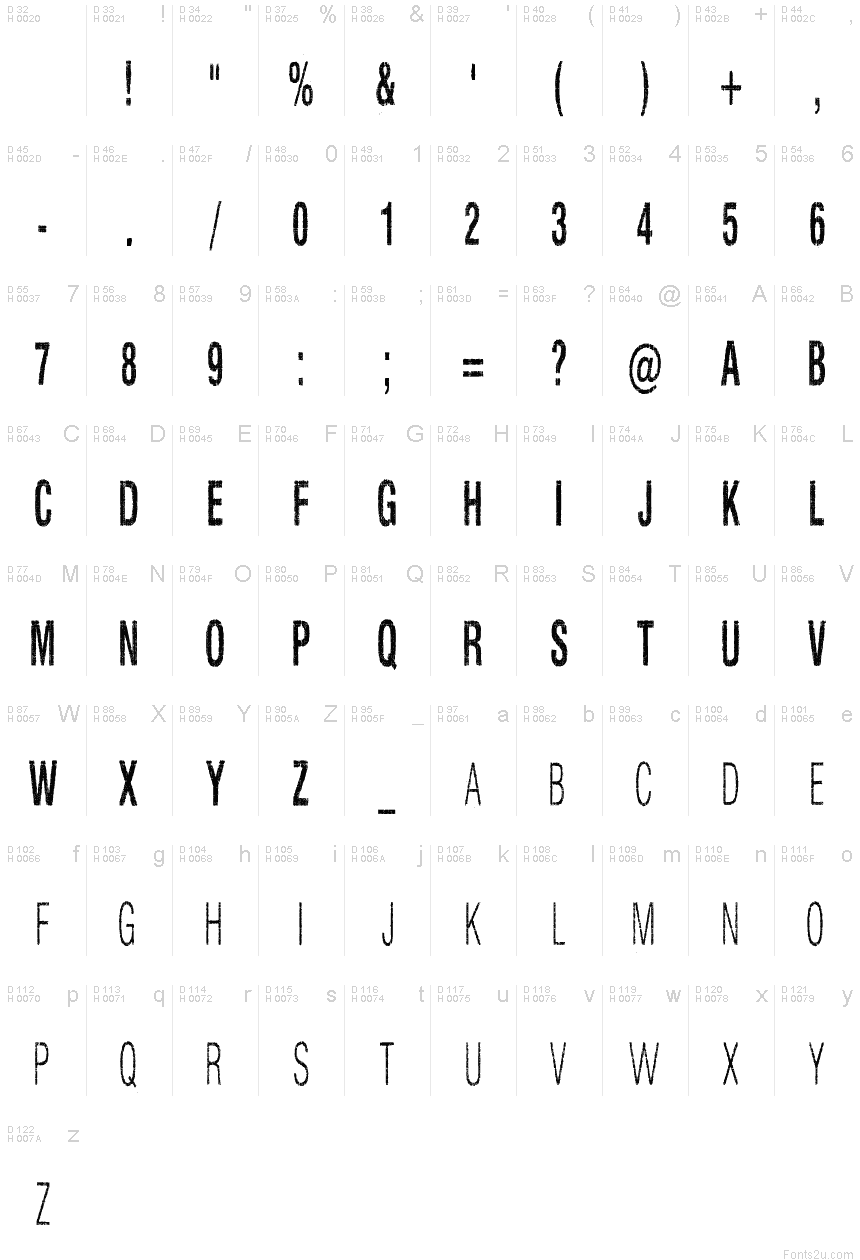
Silent Hell of Cheryl Condensed
Silent Hell of Cheryl Condensed od SDFonts to darmowy, erodowany font displayowy z surowym, kserograficznym ziarnem. Litery sprawiają wrażenie wysokich, zdrapanych i nieco nierównych, a wąskie proporcje w połączeniu z chropowatymi krawędziami nadają wielkim literom napiętego, postarzanego klimatu plakatowego.
Świetnie sprawdzi się na ulotkach undergroundowej muzyki, horrorowych planszach tytułowych, w zinach, postarzanej identyfikacji wizualnej i krótkich nagłówkach, gdzie to właśnie ta uszkodzona tekstura gra główną rolę. Jako darmowy font, najlepiej działa w krótkich ekspozycjach, ponieważ wąskie litery i połamane powierzchnie tworzą wyrazistą, nawiedzoną aurę bez potrzeby zajmowania dużej ilości miejsca.